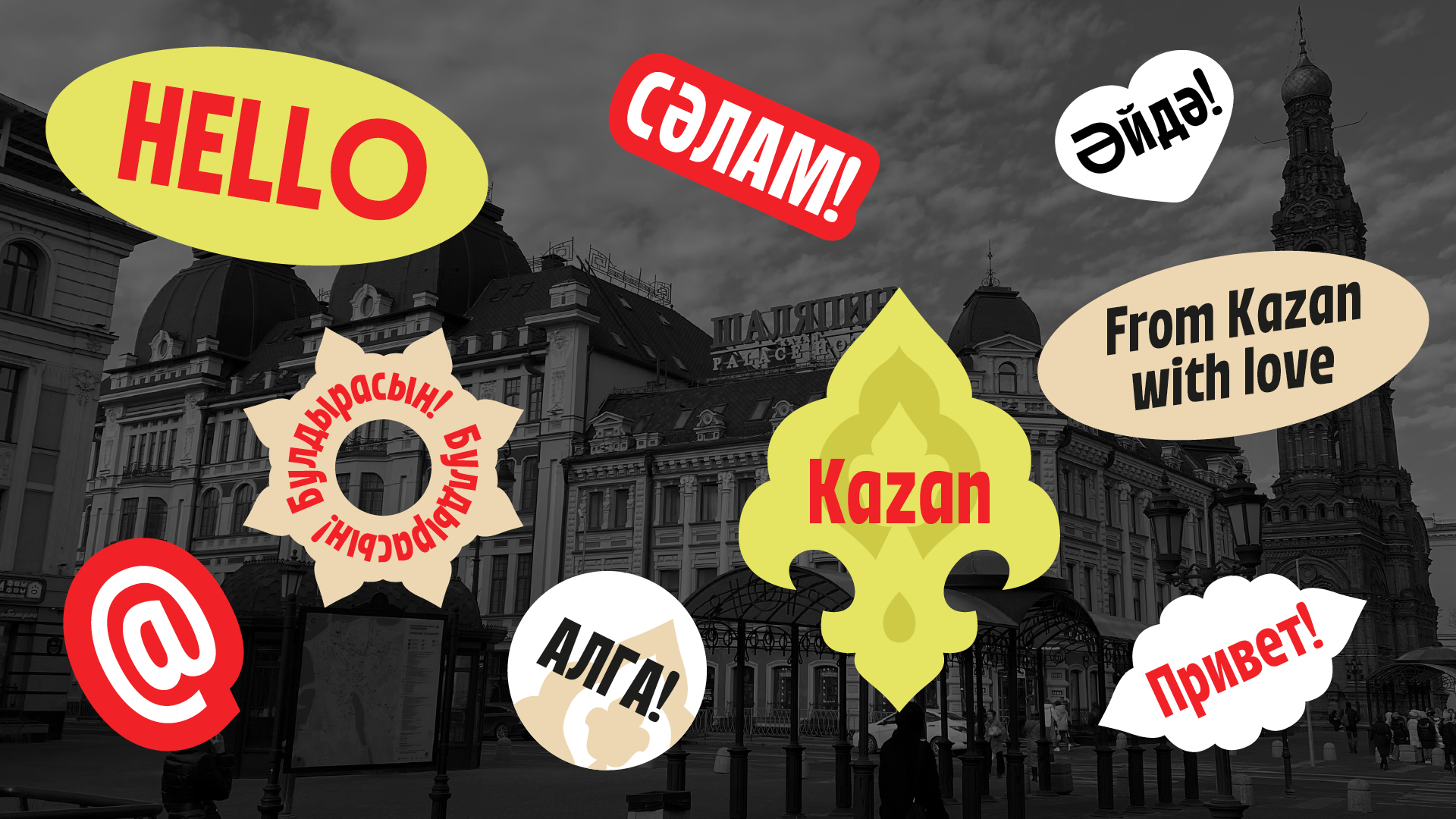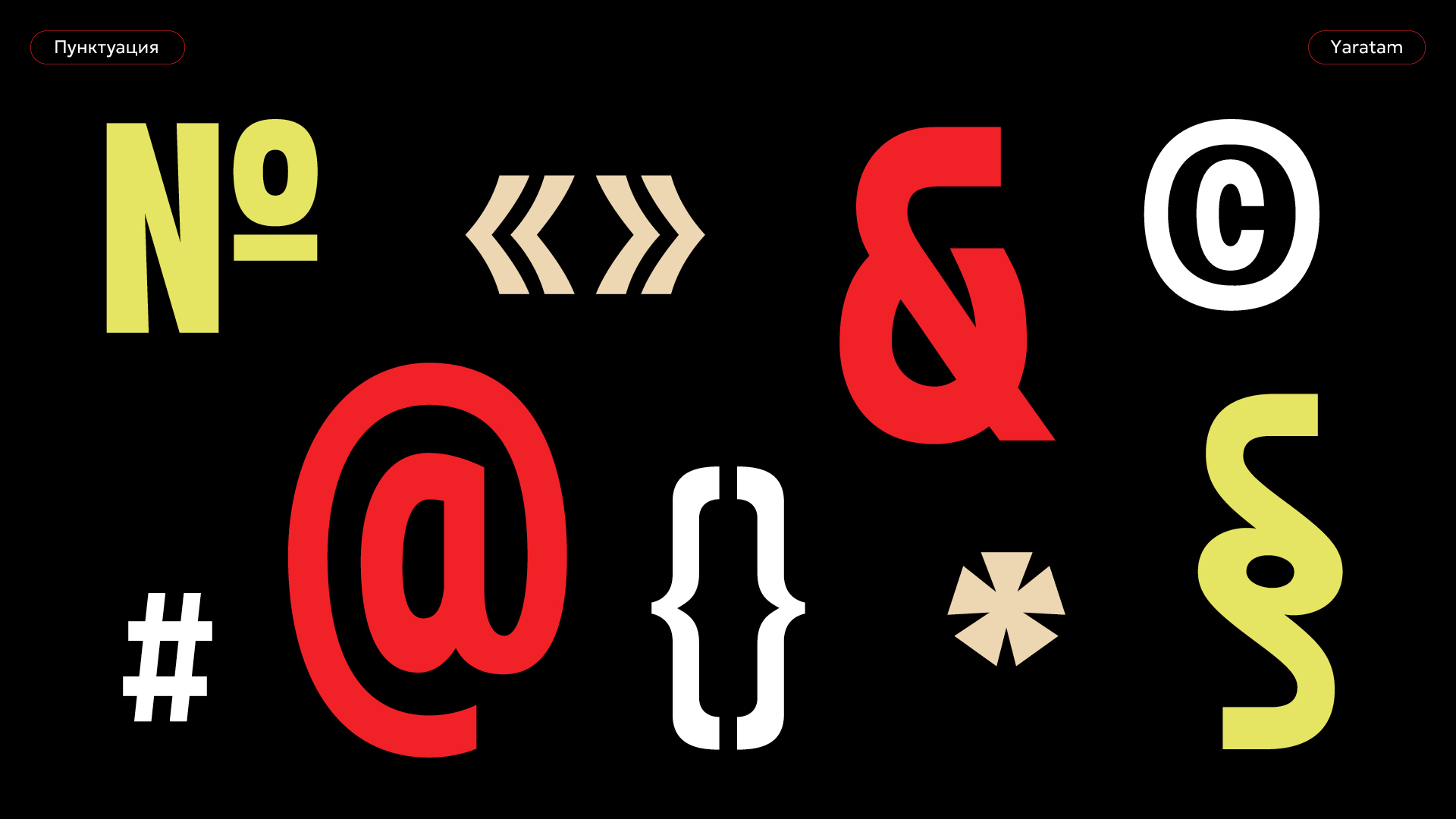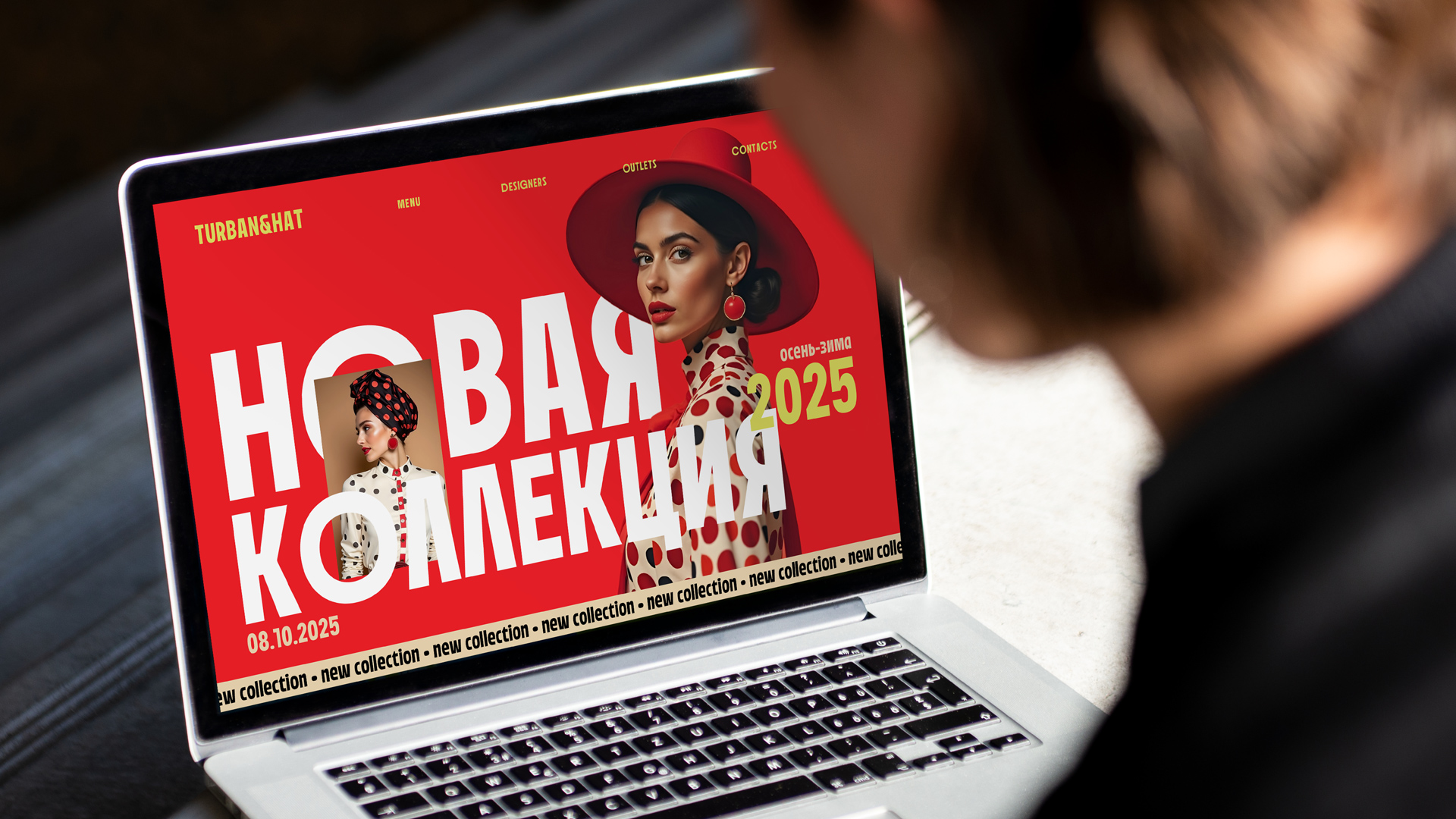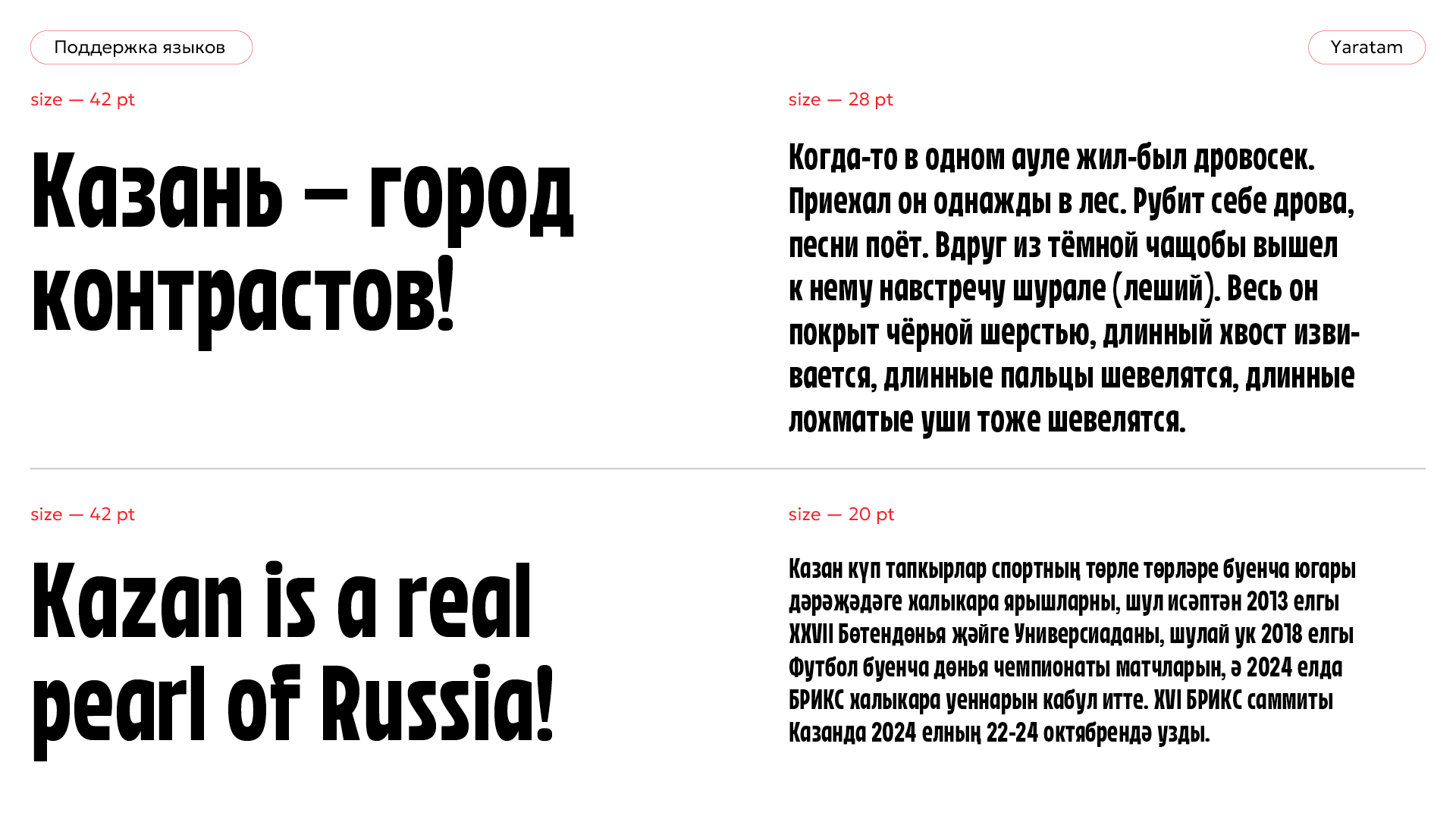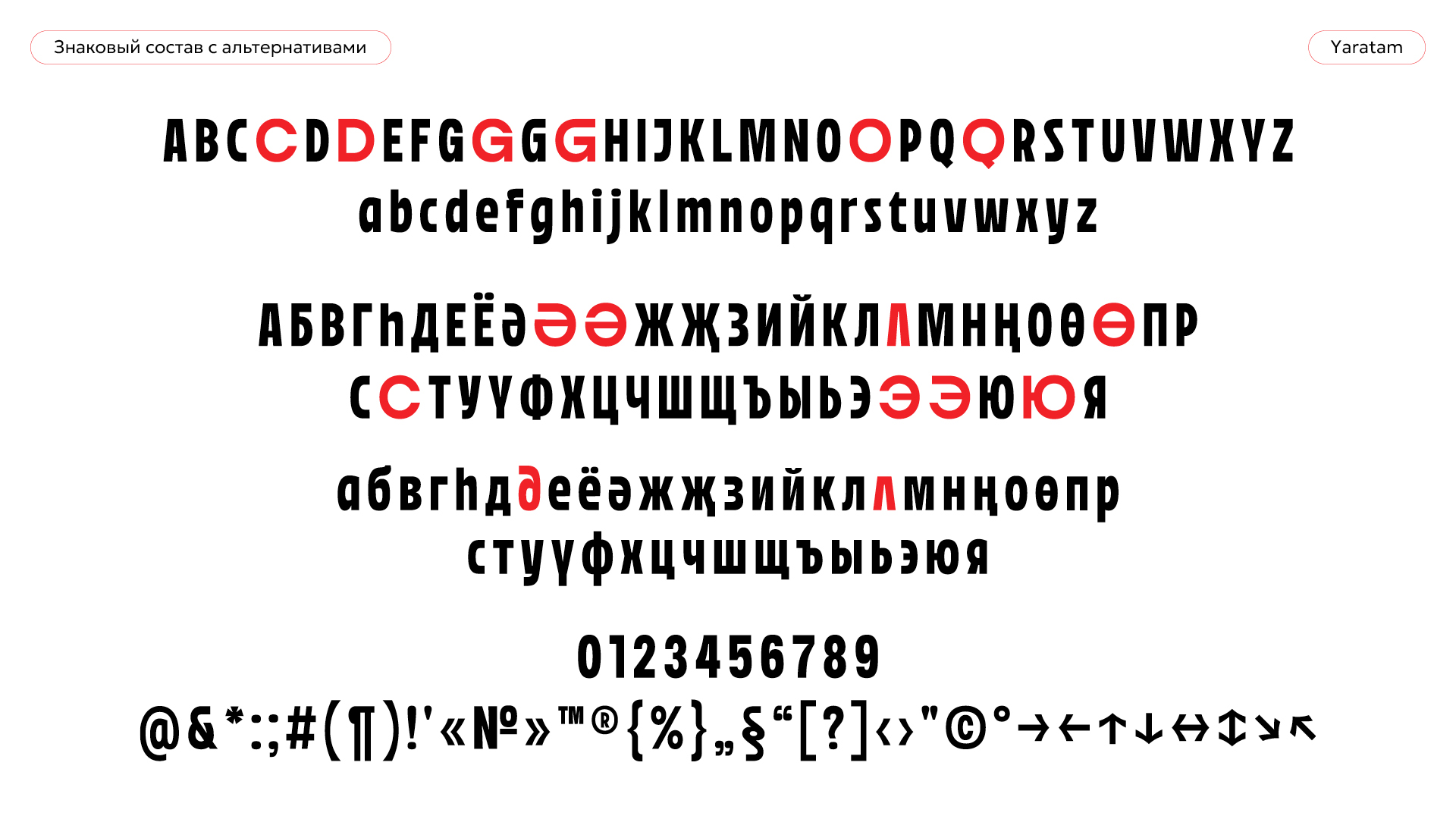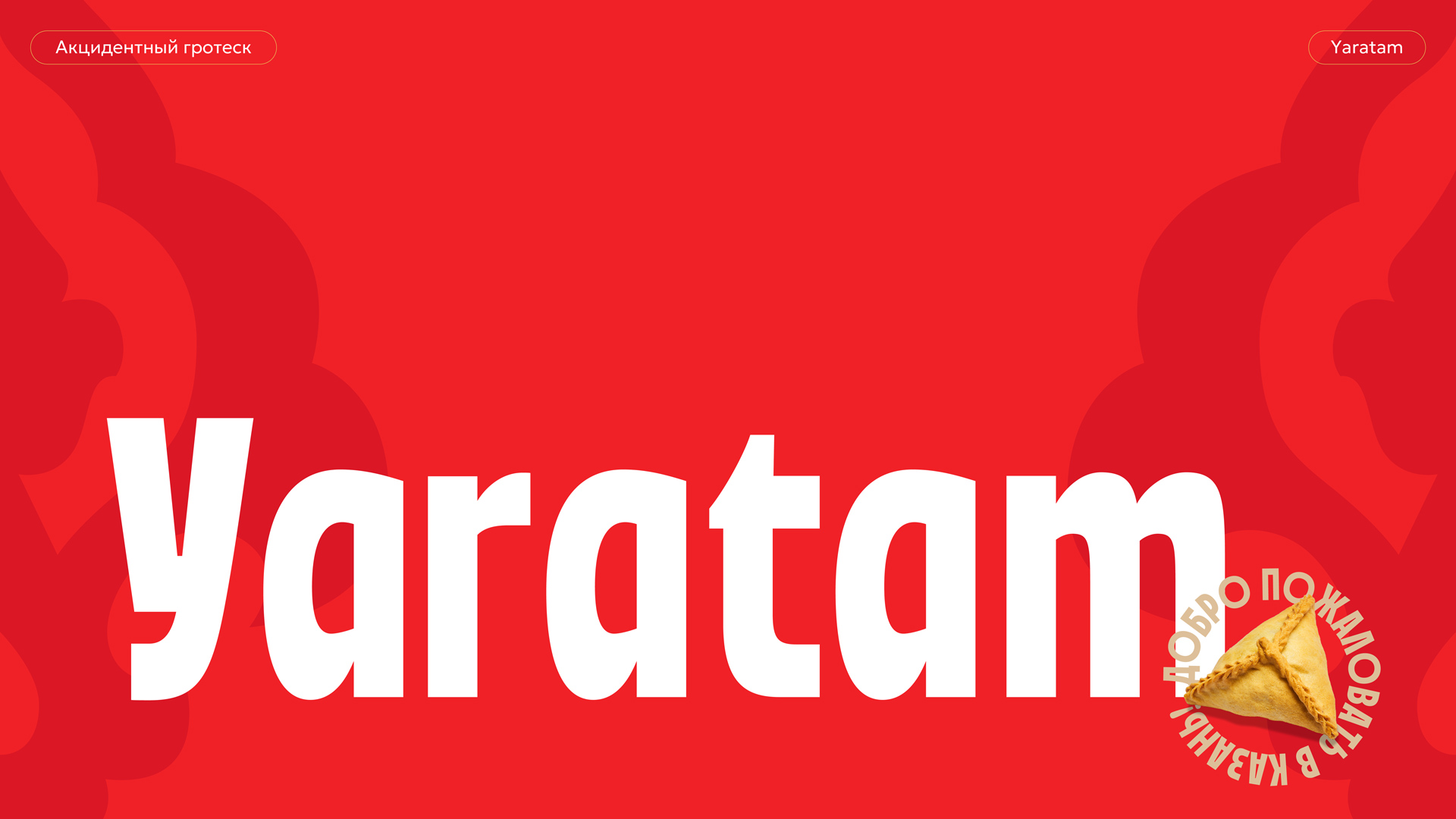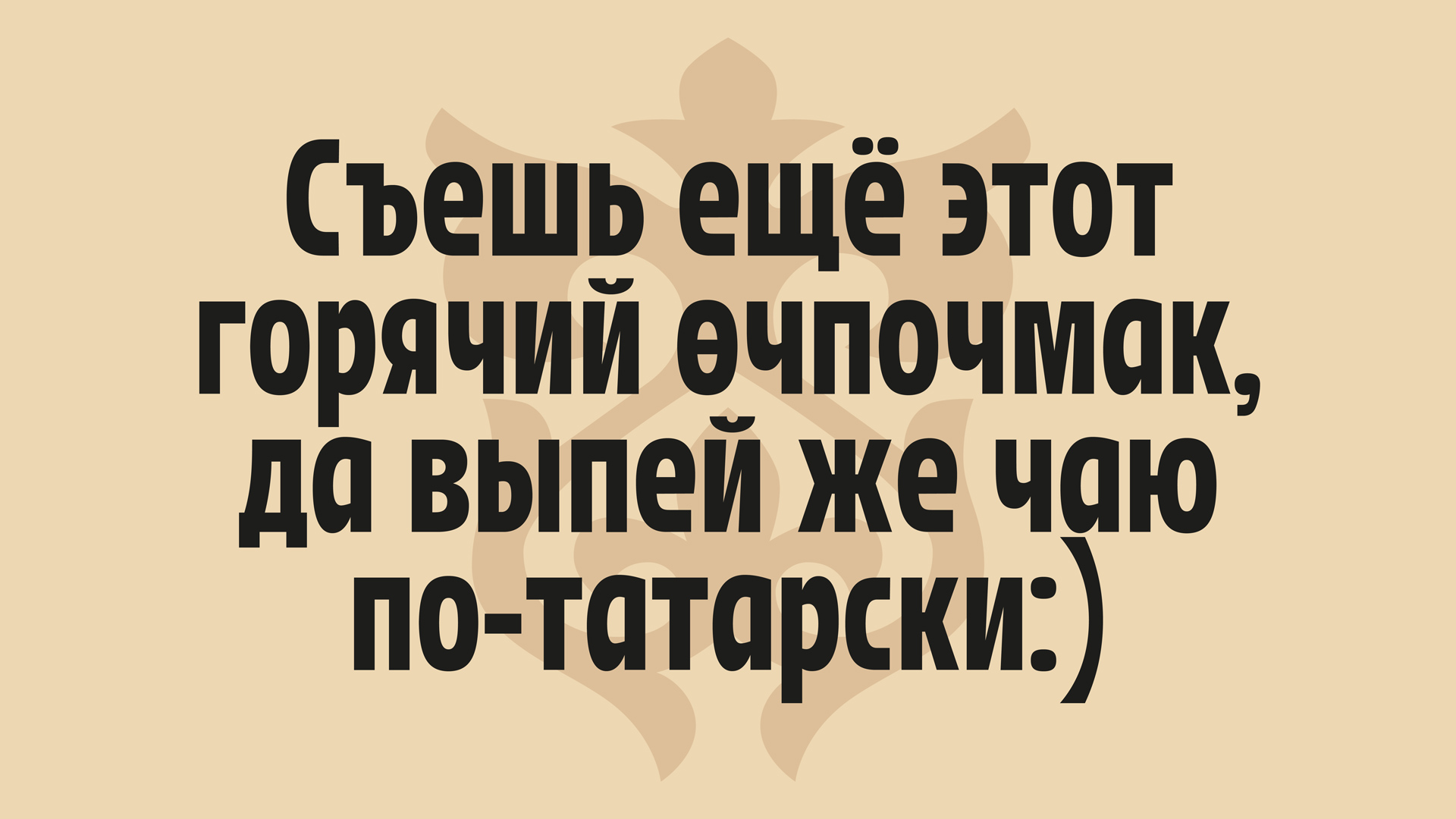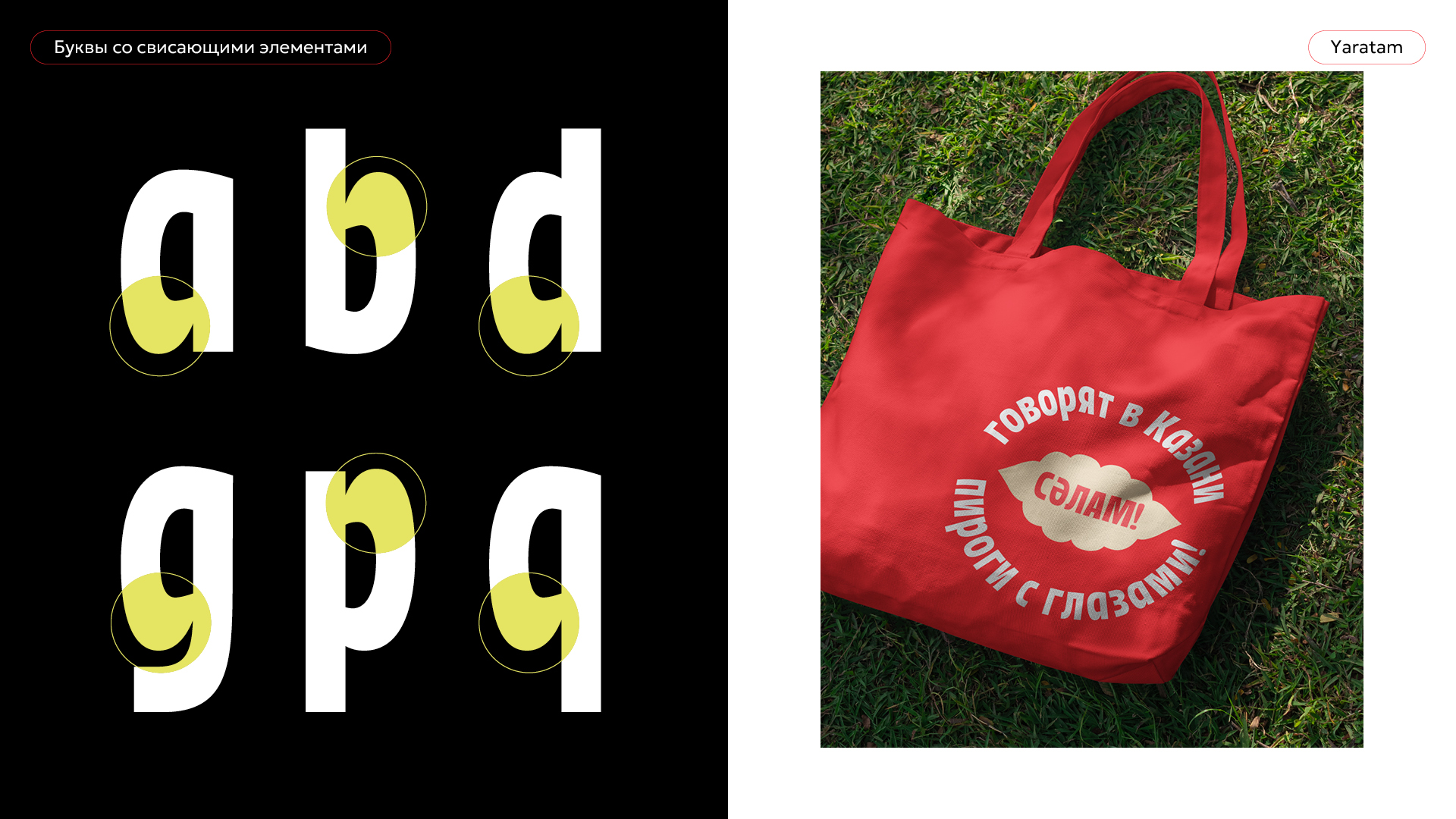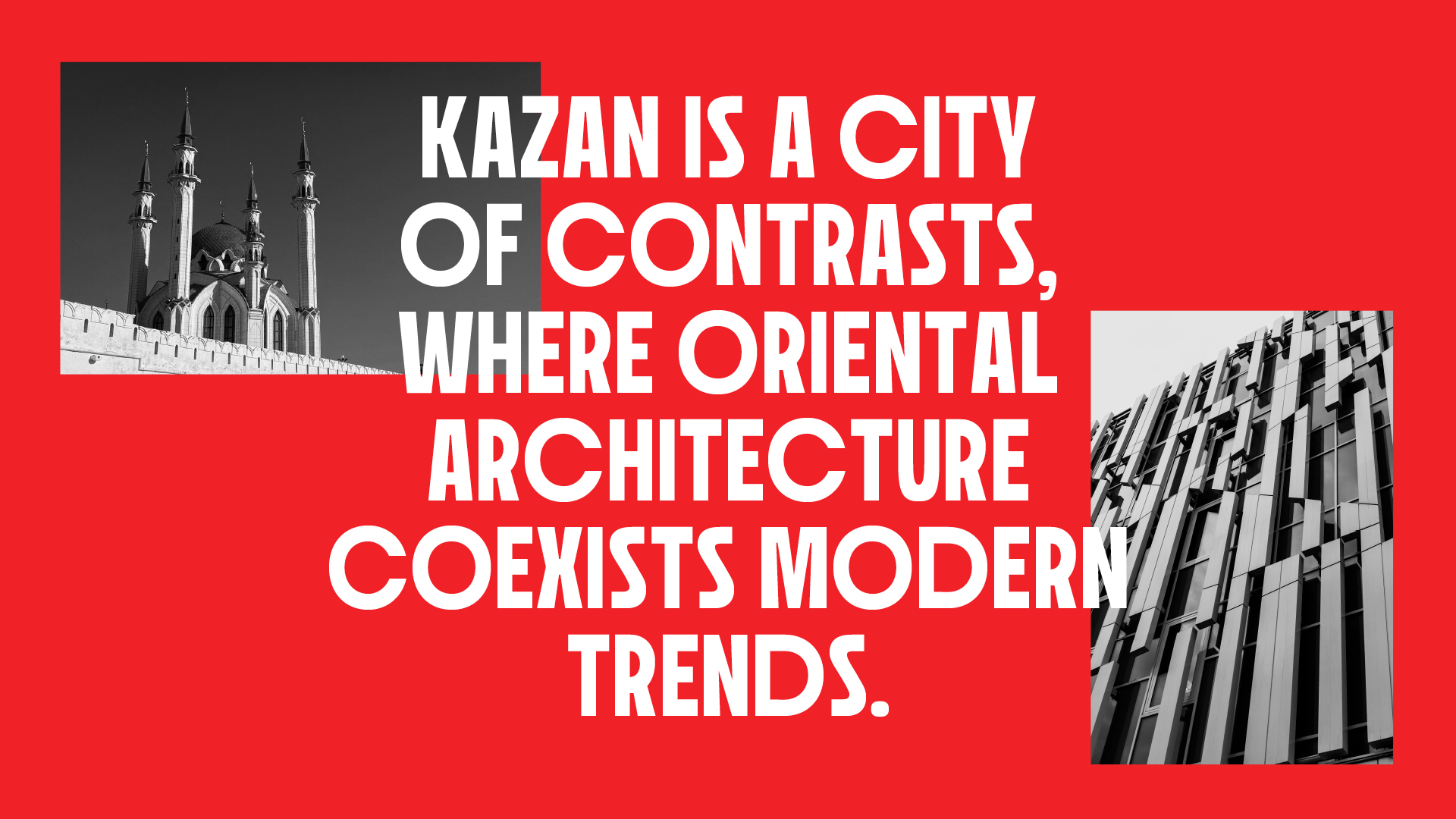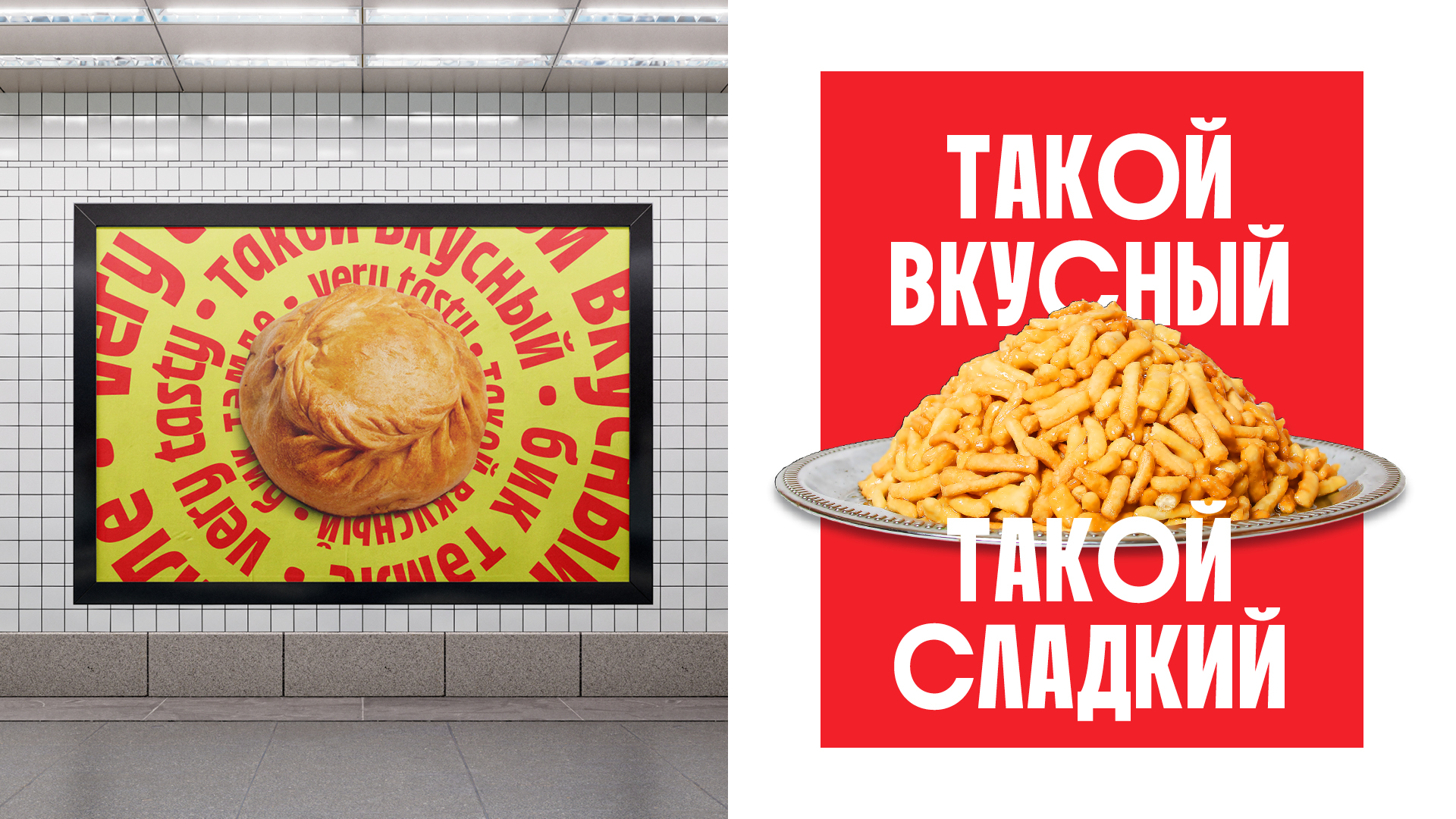
Шрифт Yaratam
Казань — это город контрастов, где восточная архитектура соседствует с европейской, а традиции татарской культуры гармонично сочетаются с современными тенденциями. Всё это послужило основной идеей при создании шрифта. Yaratam в переводе с татарского означает «люблю», так что это своеобразное признание в любви своему родному городу.
Шрифт Yaratam — это акцидентный высокий гротеск, с небольшим обратным контрастом, с зауженными пропорциями и открытой апертурой. Шрифт устойчивый и плотный, большинство знаков очень простые. Среди строчных можно встретить буквы с декоративными свисаниями.
В минимальный знаковый состав входят цифры и знаки валют, а также различные неалфавитные знаки. В стилистический сет входят прописные широкие круглые буквы. Кириллица содержит буквы татарского, башкирского и удмуртского языков. Шрифт был создан на курсе в шрифтовой студии Bolditalic.